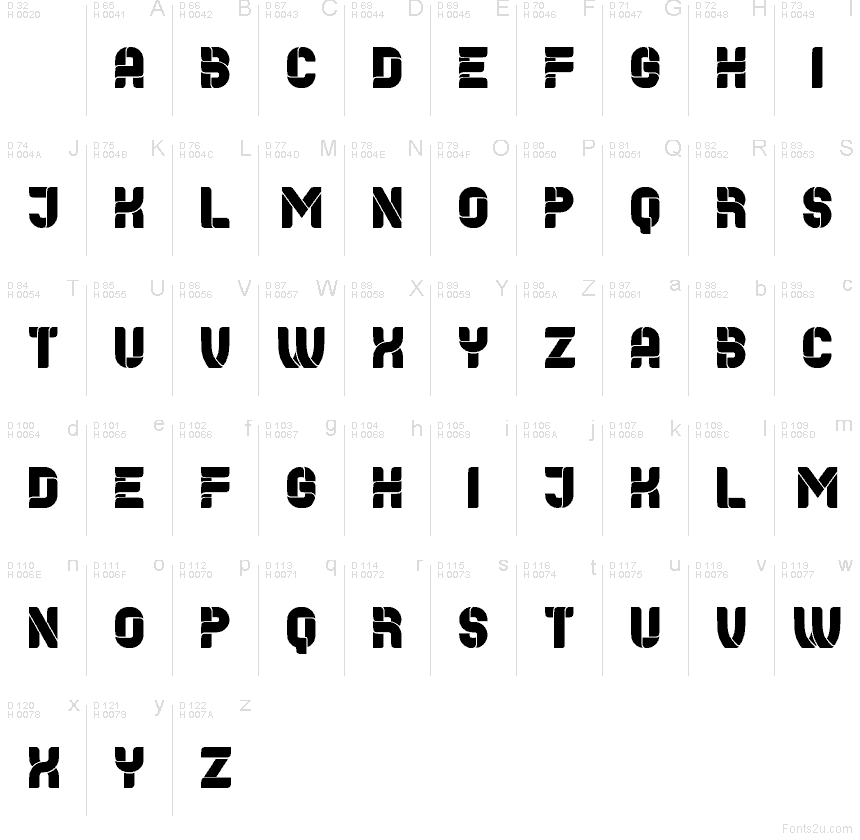
Browser Extravagant od Vladimíra Nikolića je bezplatné retro-futuristické titulkové písmo s veľkými písmenami, masívnou zaoblenou siluetou a jemnými vrezanými detailmi, vďaka ktorým písmená pôsobia, ako keby boli vytesané z jedného kusa. Štýlovo sa pohybuje na pomedzí vesmírnej estetiky 70. rokov a popkultúrnej grafiky – s mäkkými krivkami, výraznou hrúbkou a niekoľkými ostrými rezmi, ktoré dodávajú textu živý rytmus.
Toto bezplatné písmo sa hodí na plagáty, obaly albumov, festivalovú grafiku, nápadité obaly produktov či titulky v časopisoch, kde jedno krátke slovo musí niesť vizuálny štýl. Skvele funguje aj v úvodných titulkách či monogramoch, pretože písmená do seba zapadajú a vytvárajú odvážne grafické bloky, namiesto toho, aby pôsobili ako bežné titulkové písmo.